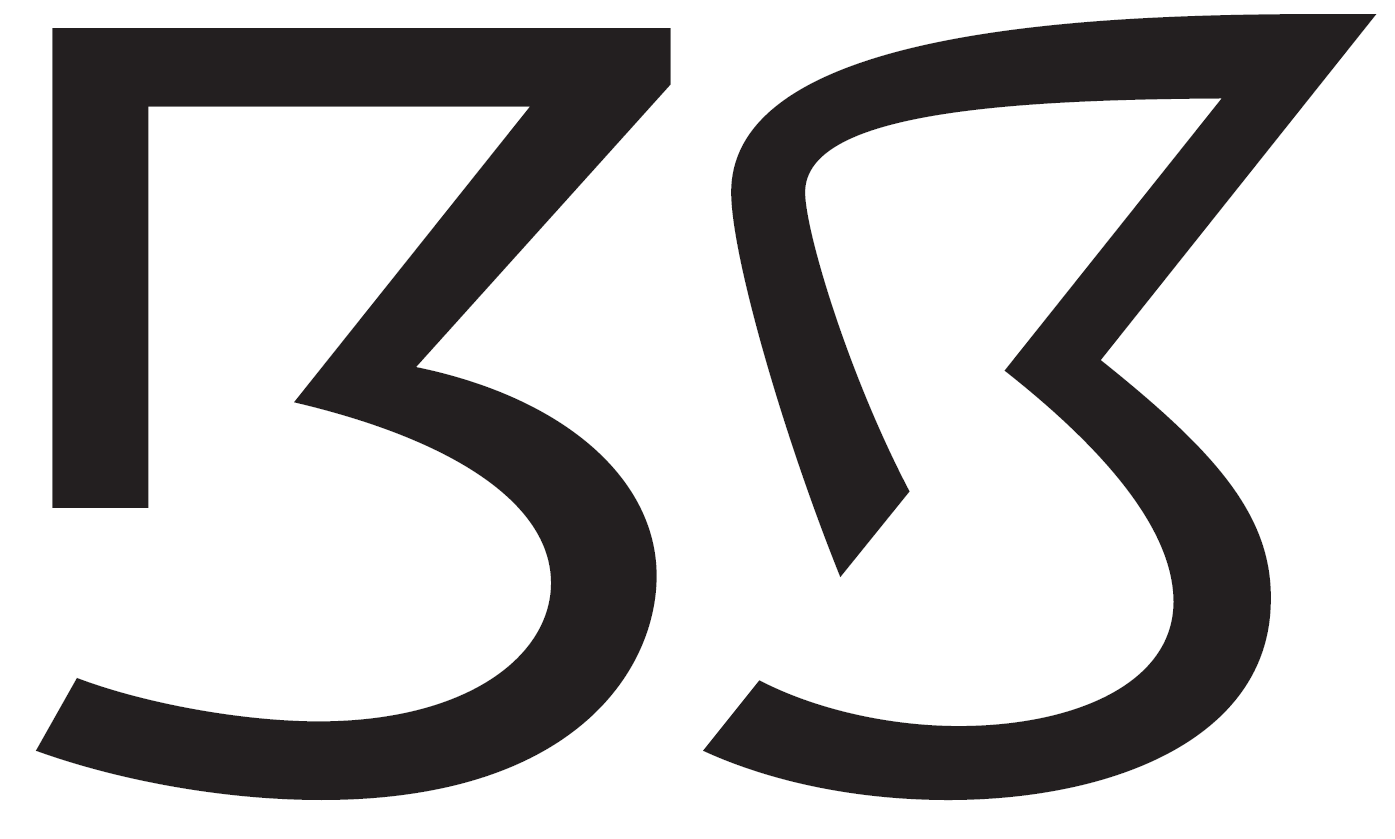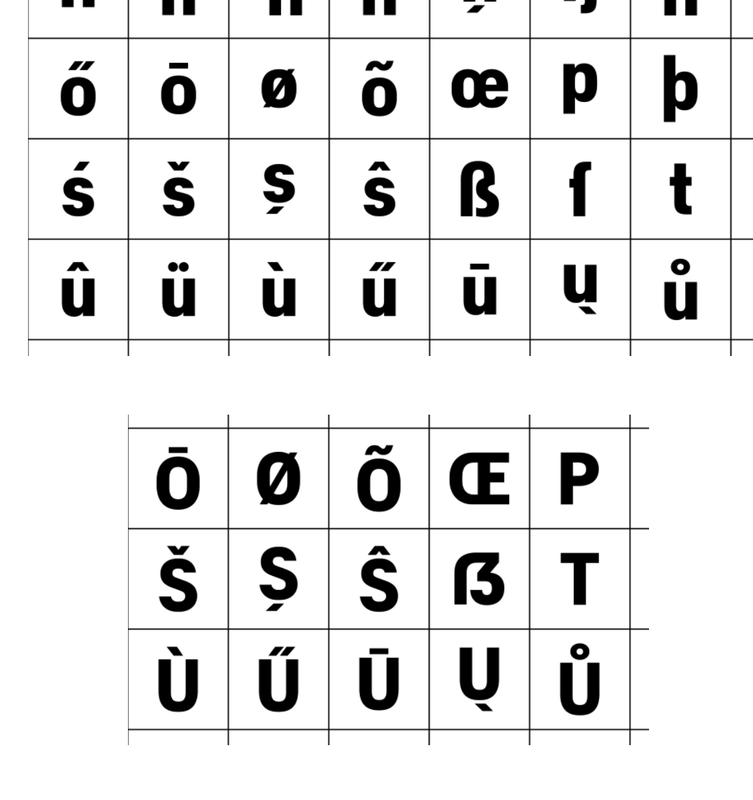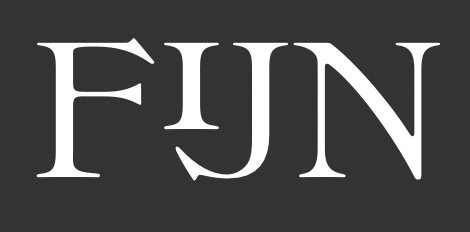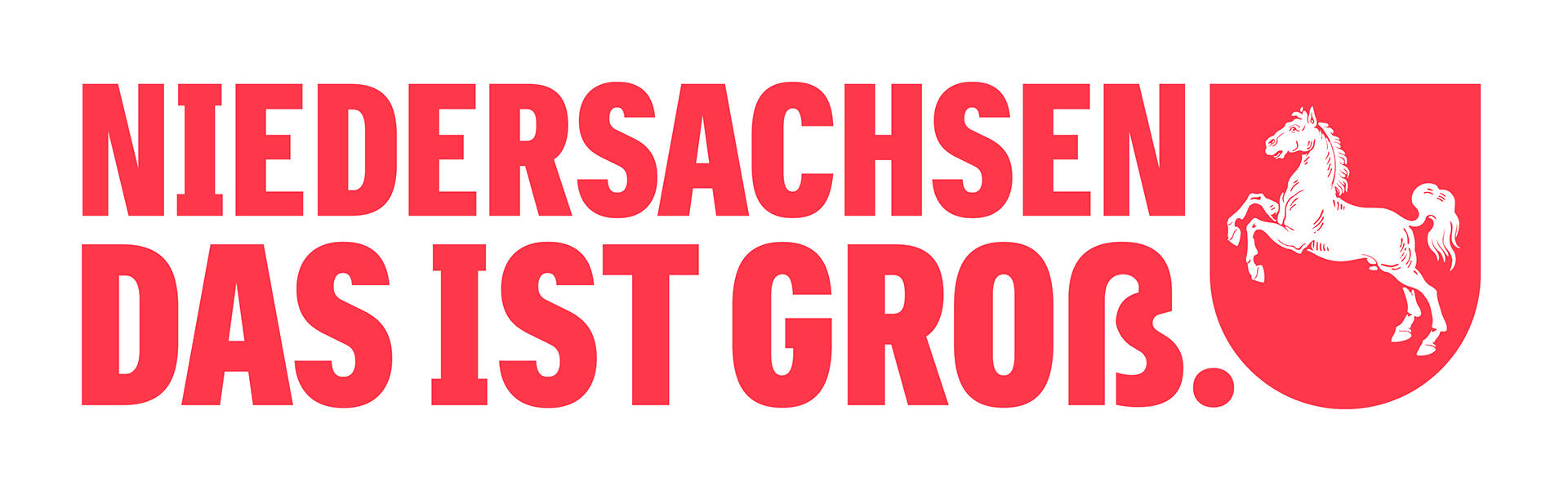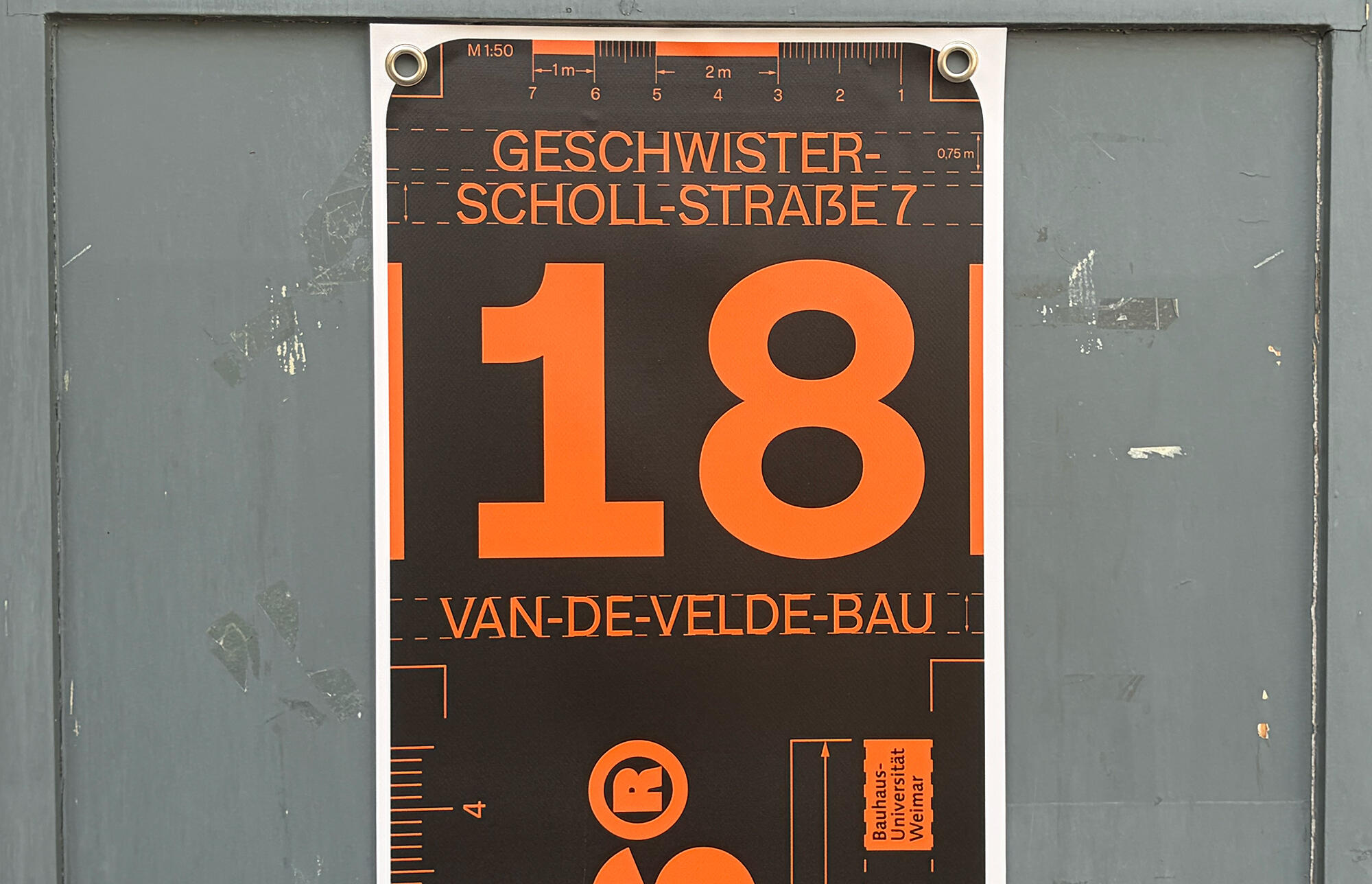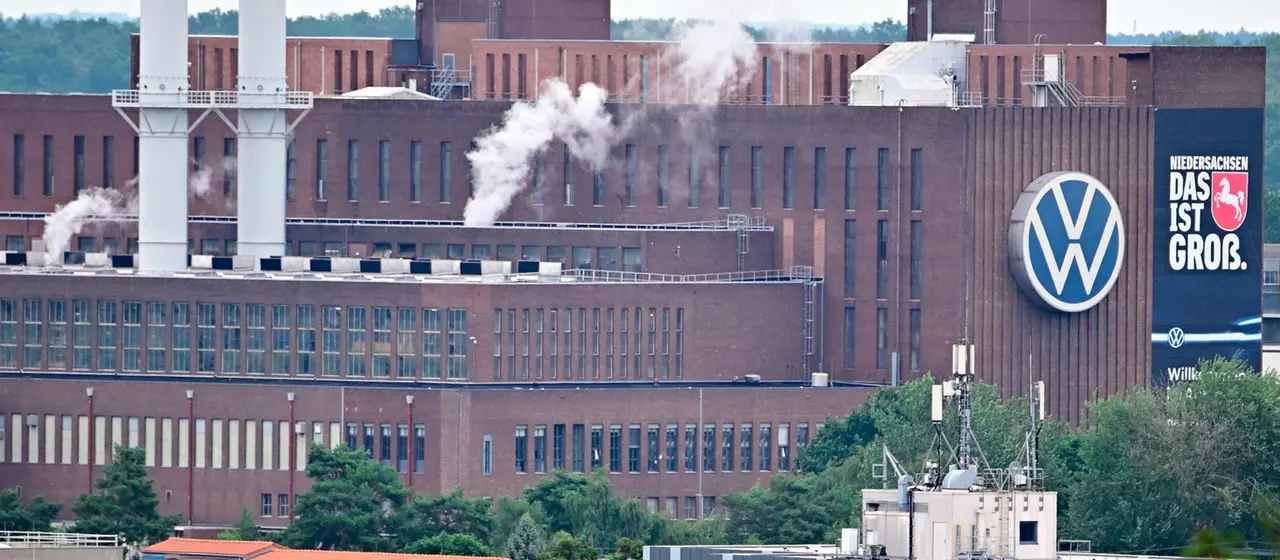
Inspiriert von dieser nicht untypischen Form in den Niederlanden?
Als Niederländer kann ich nur sagen, dass in Serifenschriften das IJ mit gekürztes I eher selten ist. Man findet es vielleicht auf Bilder mit alten Beschriftungen und bestenfalls in Schriften, die sich daran orientieren. Das gekürzte I mit Serifen ist ein Störenfried in jedes Wort in Versalien. Also etwas für Selbstverliebte und Leute mit einem Hang zur Selbstdarstellung.
Ja »semigroß« trifft es gut. Wie ein Versaleszett sieht es jedenfalls nicht aus.
Da wurde wohl vergessen, das Versal-ß an die Breite anzupassen. Ich hätte mich auch fürs kleine ß im Versalsatz entschieden. Oder für gemischten Satz.
In den breiteren Schnitten sieht das Versal-ß noch zum Rest stimmig aus, Beispiel hatte ich ja weiter oben verlinkt.
Einer der Projektbeteiligten hat darauf hingewiesen, dass das Versal-Eszett aus der Nure-Schriftfamilie vertestet, aber von der Mehrheit nicht als solches erkannt wurde. Der Argumentation kann ich in Bezug auf das originäre Versaleszett folgen.
Meine Schlussfolgerung daraus wäre allerdings gewesen, es entweder anzupassen (wie Diwarnai schreibt), oder eben komplett neu zu zeichnen bzw. zeichnen zu lassen. Die jetzige Lösung ist weder Fisch noch Fleisch.
Die jetzige Lösung ist weder Fisch noch Fleisch.
»Beyond Type« sozusagen ... 8-)
Frage: Hat jemand einen aktuellen Personalausweis, der ein echtes großes Eszett benutzt? Ich bin auf der Suche nach einer möglichst hochaufgelösten Darstellung der Anwendung.
Meines sieht einen kleinen Tick breiter aus als dein Beispiel …
Hier der Vergleich zum im Font enthaltenen ẞ
Abgesehen davon, dass das ß nicht zu den Versalien passt und das ẞ zu breit ist finde ich, dass das I sich zu wichtig nimmt.
das I sich zu wichtig nimmt
Mein erster Gedanke war, das I nimmt sich zu wenig wichtig, da die Serifen sehr zögerlich sind. Wenn Serifen, dann richtig. Oder konsequent weglassen, das ist vermutlich die geschicktere Variante.